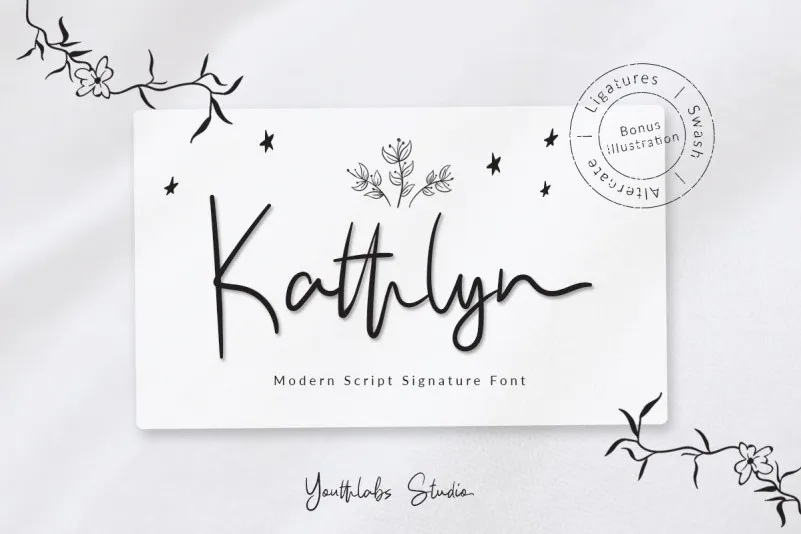
Kathlyn Signature Font – Fonte Grátis
Kathlyn Signature Font
Descubra a encantadora Kathlyn Signature Font feita especialmente para você se você quer adicionar um toque de ternura aos seus projetos. Esta elegante e moderna fonte script foi criada especificamente para dar uma sensação autêntica de escrita manual, com suas várias espessuras, alternativas, ligaturas e swashes. A Kathlyn Signature Font foi projetada em colaboração com 271 Opentype Glyphs para ter um aspecto realista da assinatura manual. Idealmente recomendada para aplicativos como casamentos, cartas, livros, cartões e muito mais, essa fonte é uma escolha perfeita para logotipos e múltiplas aplicações de projetos de design. Com a Kathlyn Signature Font, suas criações ganharão um ar autêntico de escrita manual, oferecendo um toque delicado e sofisticado aos seus trabalhos.